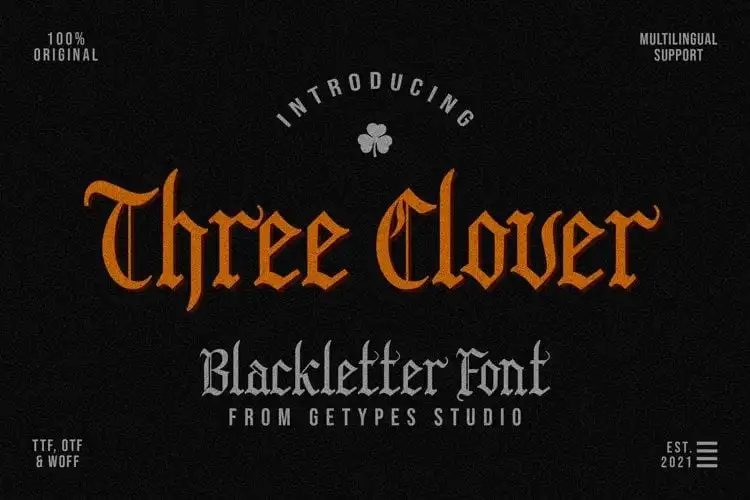
Three Clover Blackletter Font – Fonte Grátis
Three Clover Blackletter Font
A Three Clover Blackletter Font é uma criação moderna e única do Getypes Studio, adaptada para os designers que procuram uma nova perspectiva nas linhas manuscritas negras. Esta fonte traz um toque de originalidade ao seu trabalho, especialmente agradável quando se usa em aplicativos criativos como logomarcas, estampas personalizadas e até mesmo em projetos de tatuagem. A Three Clover Blackletter Font inclui tanto letras maiúsculas quanto minúsculas, assim como sinais de pontuação e caracteres internacionais, o que a torna uma opção versátil para qualquer projeto onde se deseja um charme especial nas letras. Essa fonte perfeita para design de visualização, pode ser usada tanto no seu site quanto em sua camisa personalizada ou até mesmo em um studio de tatuagem criativo. A Three Clover Blackletter Font é uma excelente escolha para quem busca algo mais além do estático e deseja incorporar a emoção da literatura manuscrita em seus projetos.